圆体大全,6 款免费圆体和 6 款付费圆体合集
在我们的日常生活中,圆体字无处不在,从儿童读物到科技产品界面,从咖啡馆招牌到时尚品牌Logo,当你在为这些场景设计时,找到合适的圆体是不是比较耗时,本文就给大家汇总了 12 个不同的圆体字体,包含了 6 款免费商用和 6 款授权使用,可以根据自己的需求进行选择。
一、什么是圆体
我们先不去定义圆体,先来想想是否这些场景,幼儿园老师板书上的可爱文字,某个品牌的可爱 Logo,App 里那些让人倍感亲切的按钮文字。没错,圆体字最大的特点就是其笔画圆润、转角柔和,通常没有尖锐的棱角。这种形态上的特征,赋予了圆体字独特的视觉和心理效应。
圆体的特点
- 圆润的形状则给人带来安全、舒适的感觉。圆体字的柔和笔画,能够降低视觉上的“冲击力”,让人感到放松。
- 圆体字因此也被赋予了友善、包容、易于接近的形象,非常适合需要建立情感连接的品牌或产品。
- 俏皮、活泼的特点,这使得它们在儿童产品、年轻时尚品牌和娱乐产业中备受青睐。
圆体的适用场景
- 许多知名品牌,尤其是那些希望传达亲和力、创新精神或年轻态度的品牌,都会选择圆体字作为其品牌标识。
- 食品、饮料、化妆品等产品的包装上,圆体字能让产品看起来更美味、更可爱、更具吸引力。
- 手机App、网站、智能设备的界面中,圆体字能够提升用户体验,让信息阅读更舒适,按钮更友好。
- 在需要吸引眼球、传达轻松愉快信息的广告中,圆体字是绝佳的选择。
- 圆体字因其可爱的形象,是儿童读物、玩具包装、教育App的首选。
- 许多潮流品牌和生活方式杂志,也喜欢用圆体字来营造轻松、舒适的氛围。
1、有爱圆体
有爱圆体是一款风格温馨、圆润饱满的中文圆体字体。其笔画圆滑柔和,线条厚重而富有弹性,整体字形亲和力强,极具现代感和人情味,适合传递温暖友善的品牌形象。
有爱圆体线条圆润,视觉柔和,给人以舒适愉悦的阅读体验,适合儿童读物、亲子产品包装、公益广告及生活服务类品牌。
2、江城圆体
江城圆体是一款兼具现代感与传统韵味的圆体字体,笔画圆滑且结构均衡。字体设计注重细节,整体字形端庄且富有韵律感,在圆润之中融入稳重气质。
江城圆体字形稳健,容易识别,适合长时间阅读。适用于城市宣传、文化活动、广告海报及品牌视觉识别系统。
3、猫啃网糖圆体
猫啃网糖圆体字形圆润但不失个性,极具辨识度,风格俏皮,适合互联网、游戏、动漫及潮流品牌宣传。
4、江城知音体
江城知音体是一款融合书写感与现代圆体元素的字体,笔画流畅而自然,带有手写的韵味,整体风格灵动而不失稳重,适合表达亲切、自然的品牌特质。
江城知音体书写感强烈,易于表达情感与亲和力。适合文化传媒、生活服务、教育培训等领域应用。
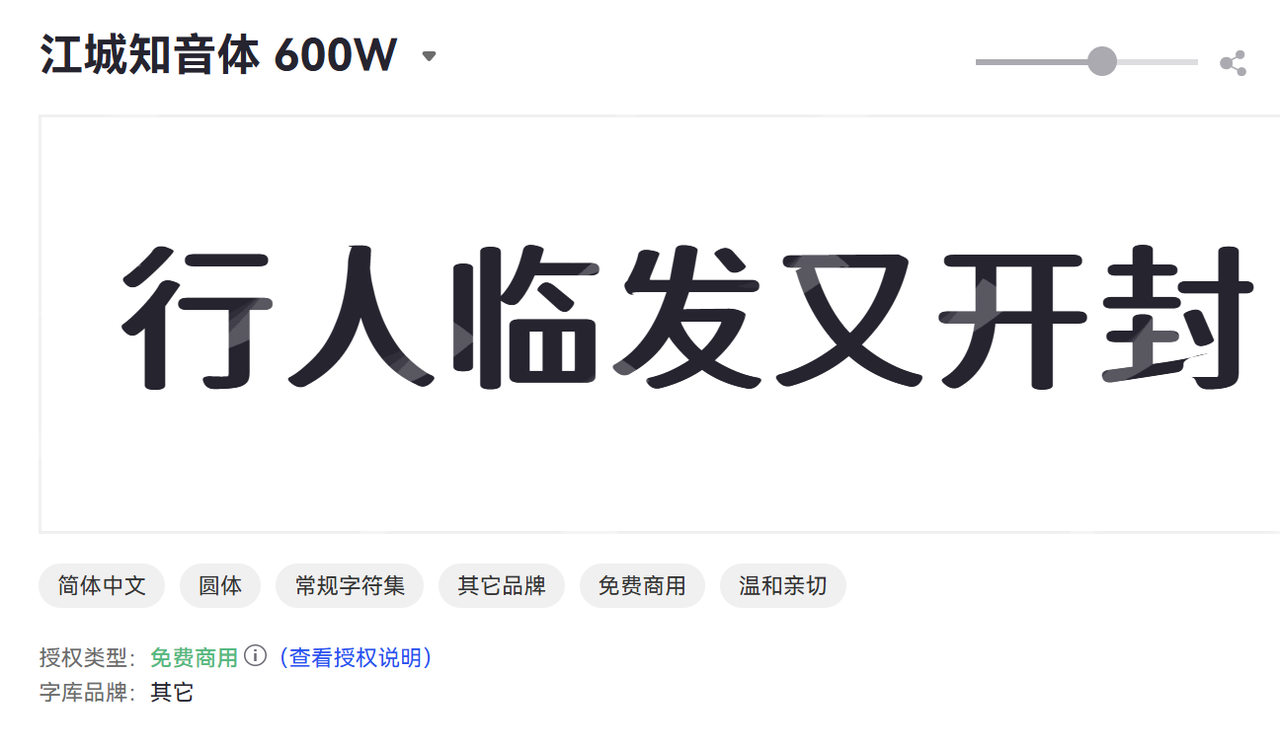
5、优设鲨鱼菲特健康体
优设鲨鱼菲特健康体是一款专为健康、运动及医疗领域设计的现代圆体字体,字体结构均匀,线条圆润且富有力量感,强调简洁与易读。
优设鲨鱼菲特健康体视觉清爽,具有专业和活力感,适合健身品牌、医疗机构、健康产品及运动赛事宣传。
6、优设好身体
优设好身体字体延续了优设系列简洁圆润风格,专注于传达健康、活力与舒适感。字体线条饱满,笔画柔和,整体亲和且现代。优设好身体应该很多设计领域的朋友都用过,视觉传达健康舒适的品牌理念。适合健康产品包装、生活方式品牌、健身相关设计。
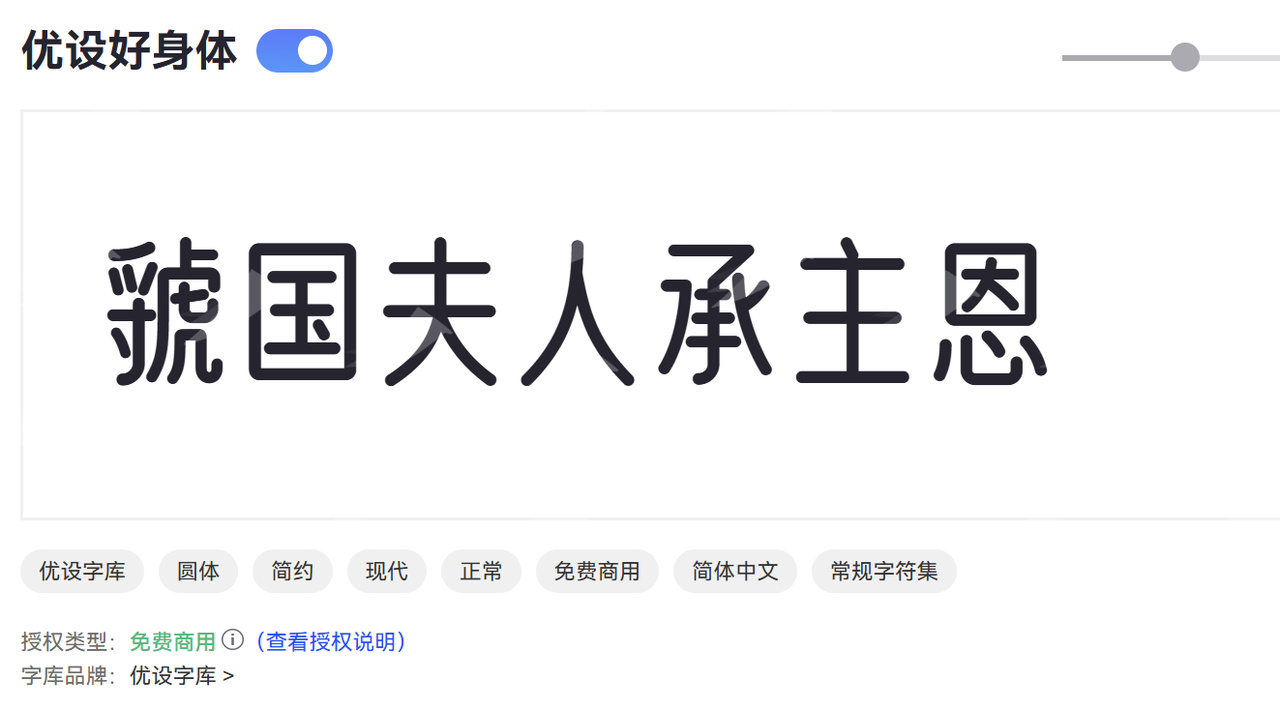
1、点字胖嘟
这款字体真的非常可爱,个人非常喜欢,圆润饱满的字体,弧线圆滑,笔画粗壮,设计风格童趣十足,适合用来表达活泼与亲切感。字形圆润且厚重,视觉冲击力强。适合儿童品牌、卡通设计、玩具包装、亲子产品等。
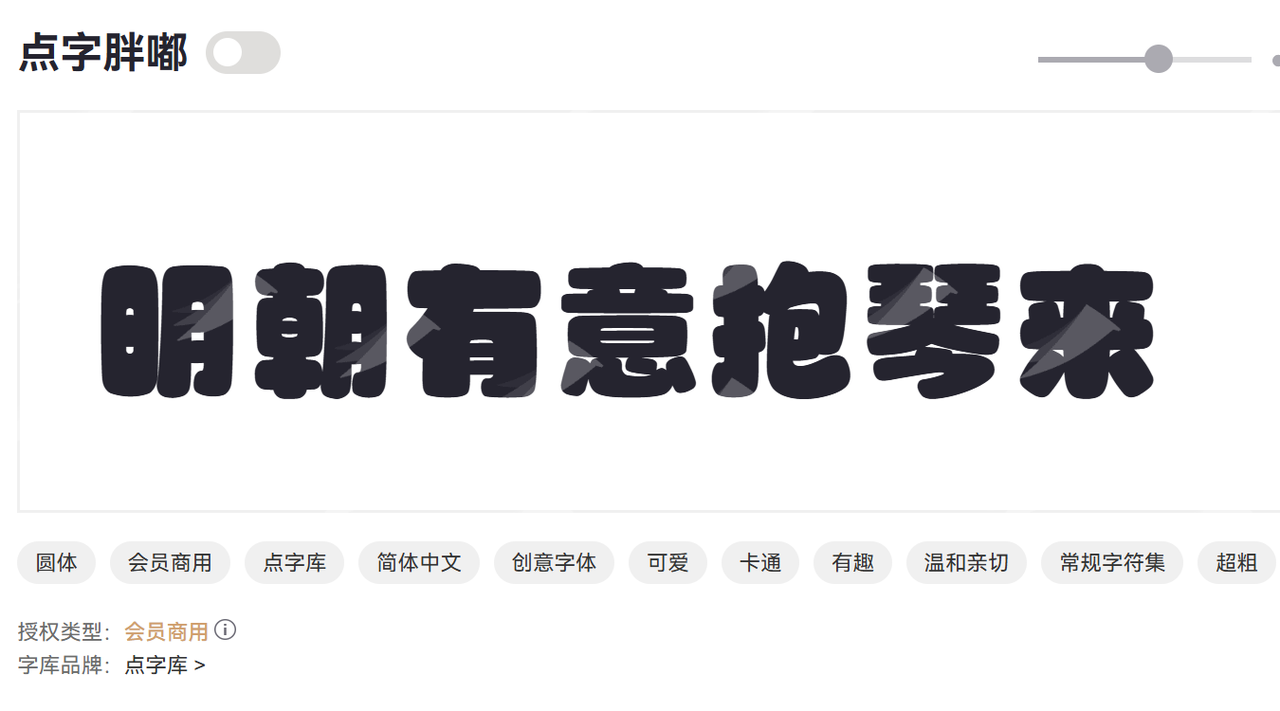
2、汉仪晓波花月圆
汉仪晓波花月圆是一款结合传统与现代元素的圆体字体,带有细腻的笔触和圆润的结构,整体柔和而富有韵味,适合高品质设计项目。比如,我在品牌设计中比较常用这款字体。
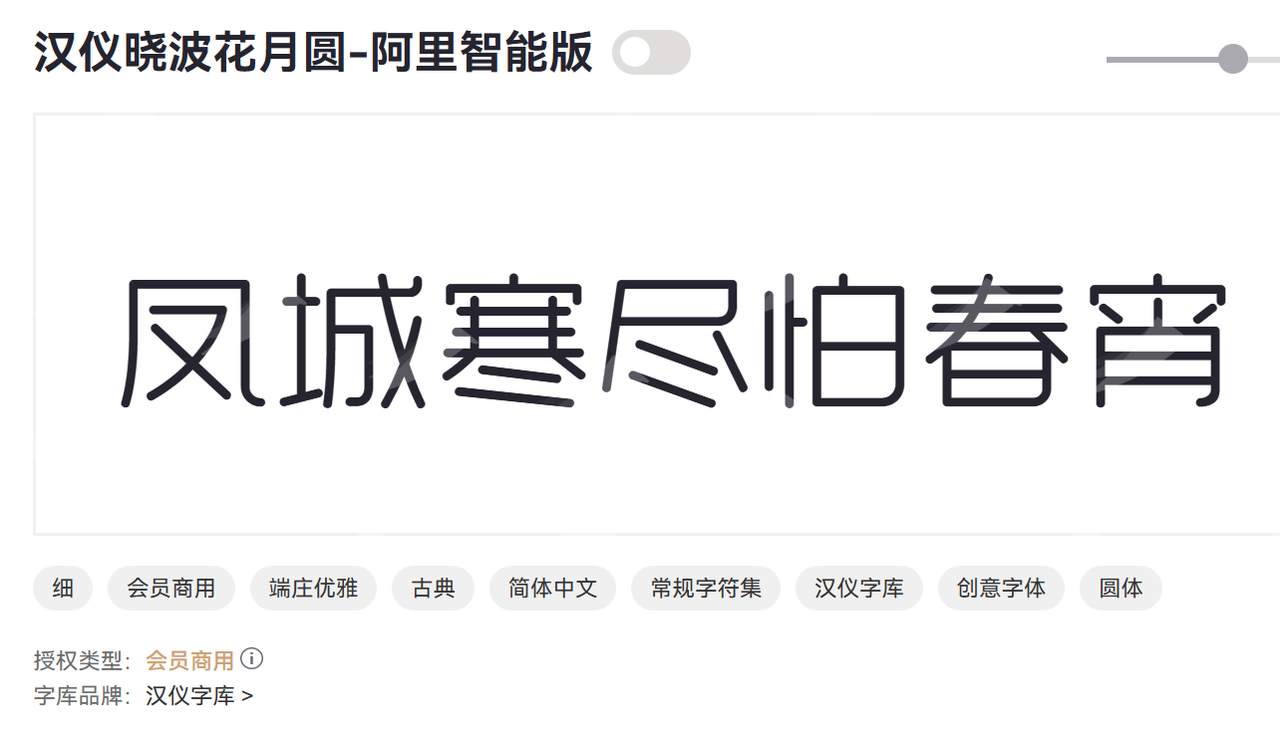
3、点字乐圆体
点字乐圆体字形柔和,富有动感,提升品牌亲切度。适用于广告设计、儿童教育、娱乐内容。
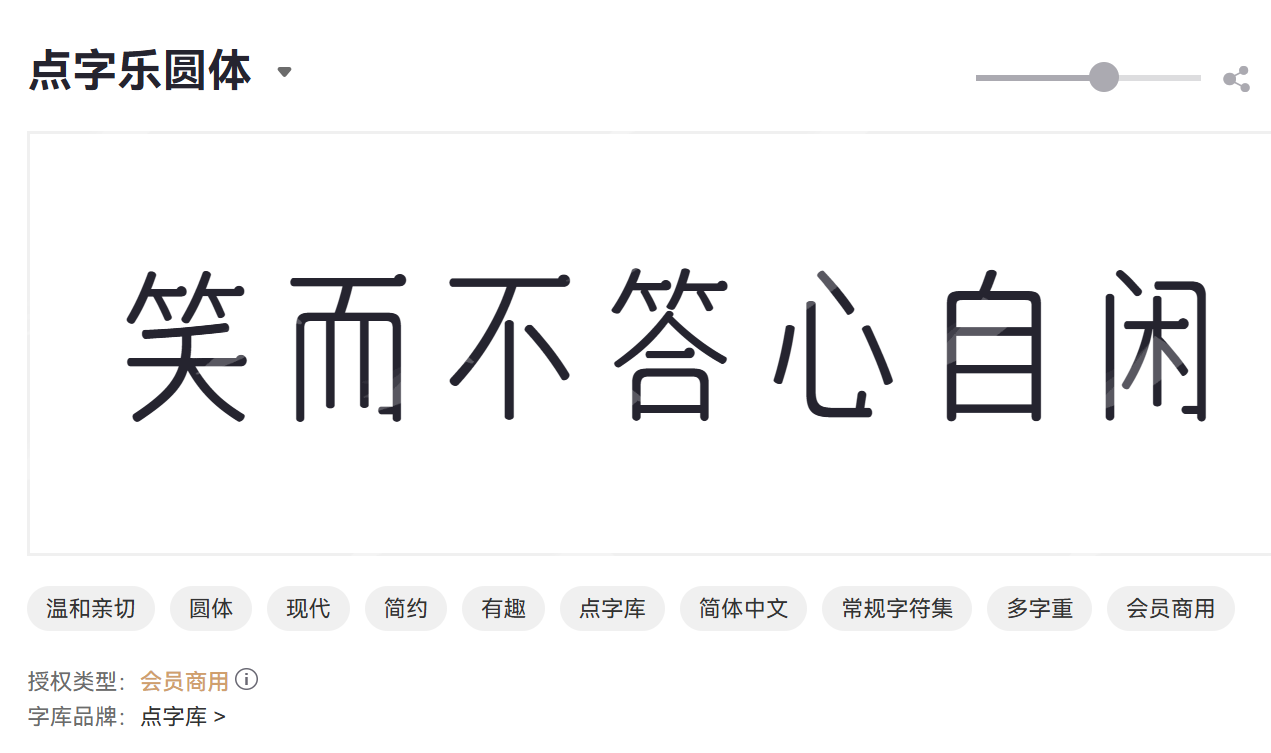
4、点字悦动
点字悦动是一款富有节奏感和动感的圆体字体,线条流畅自然,整体设计轻松愉快,适合表现青春活力和现代感。
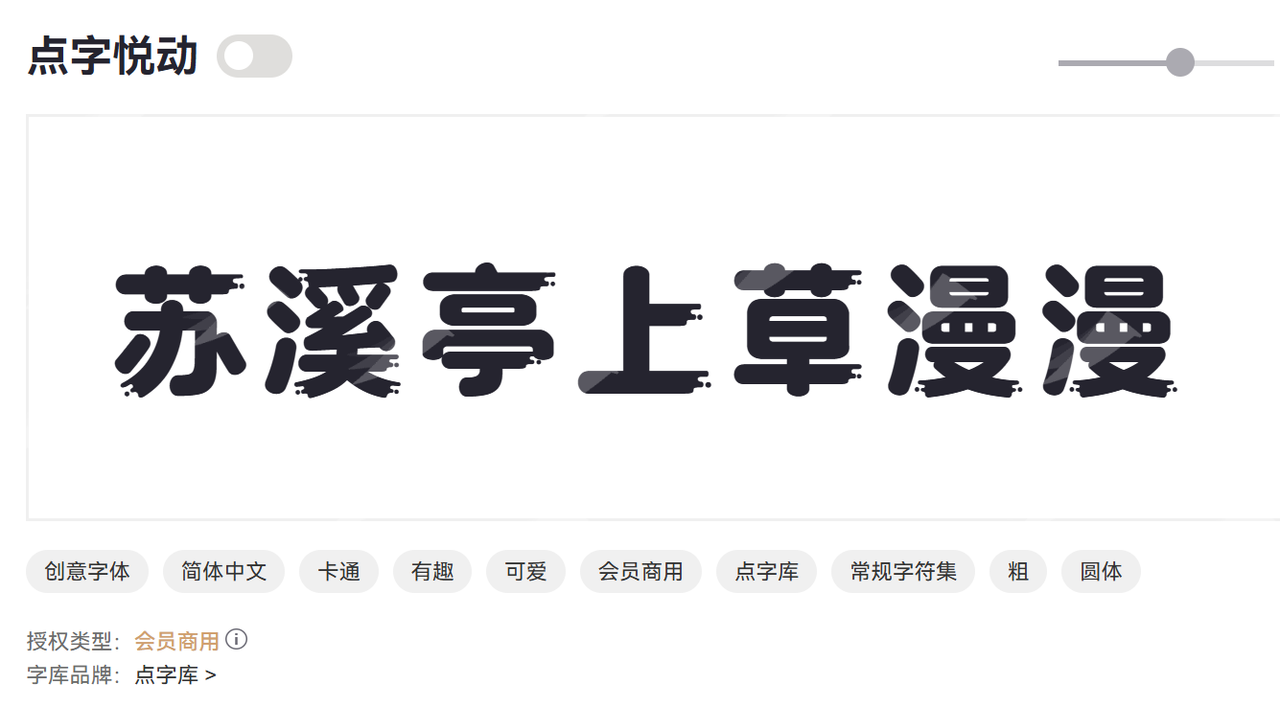
5、点字艺圆
点字艺圆是一款结合艺术感与圆润设计的字体,笔画柔和且富有表现力,适合创意设计及艺术类品牌应用。
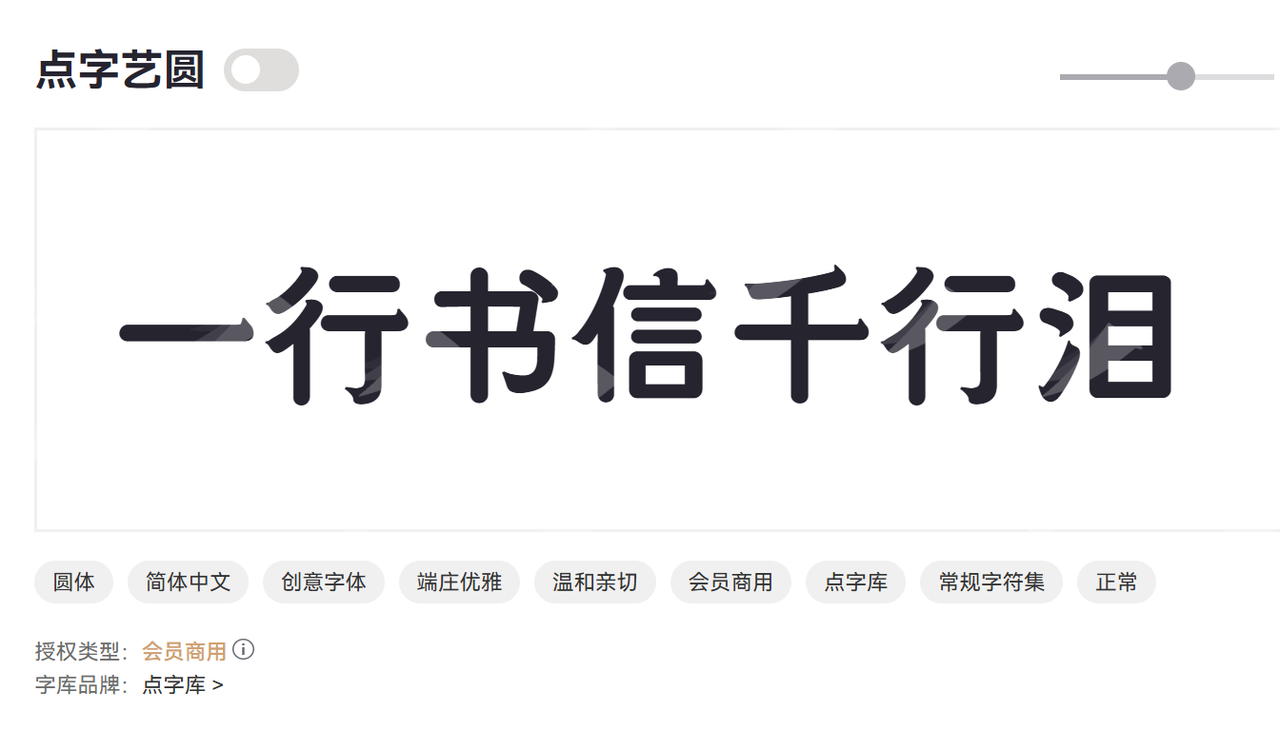
6、点字朗润体
点字朗润体是一款线条流畅、结构均衡且圆润细腻的字体,整体风格明快且富有表现力,兼顾专业与亲和力。适合教育出版、广告设计、企业宣传等多种场景。